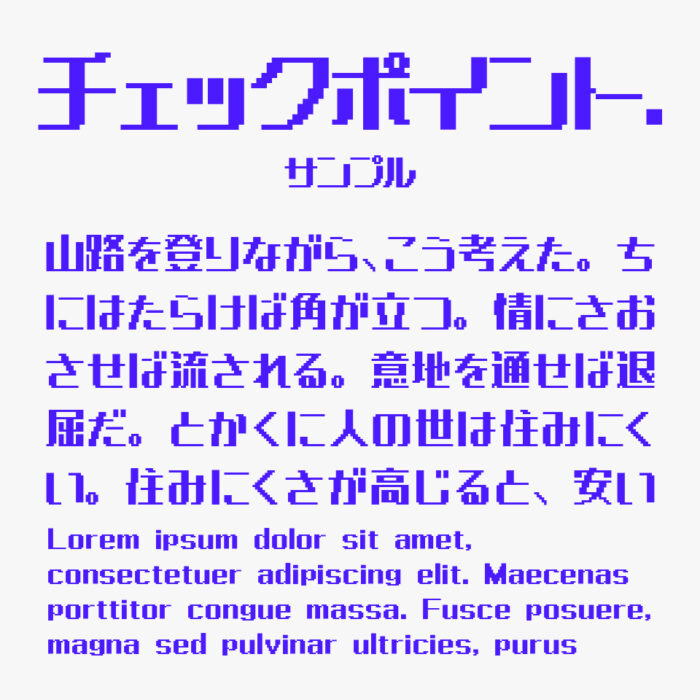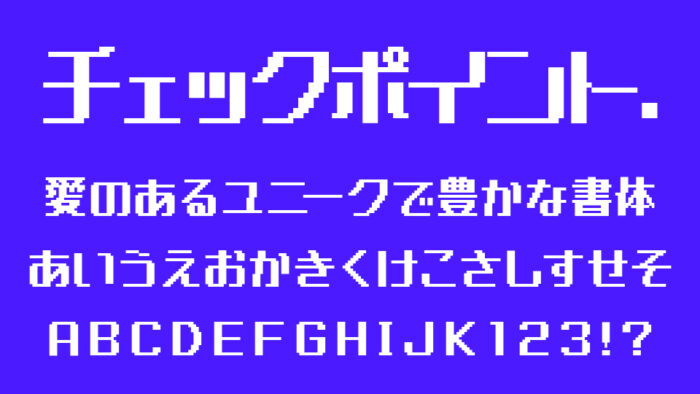
チェックポイント.(ピリオド)フォントは、「チェックポイントフォント」をベースとして、ビットマップフォント風に再構築して制作されたドットフォントです。
縦線は太く、横線は細めにデザインされており、太さのコントラストが効いており、モダンな雰囲気の中に少しの遊び心も感じられ、さらにドット感があることで、レトロさとデジタルな風合いが絶妙に調和した、とてもステキなフォントです。